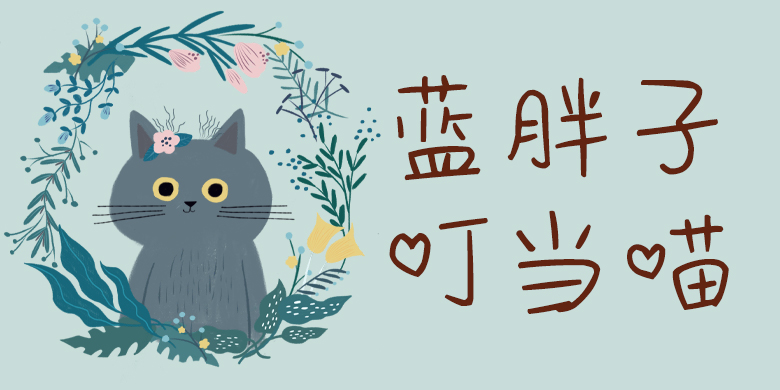
方正手迹-蓝胖子叮当喵
方正手迹-蓝胖子叮当喵,这款字体结构工整、笔画清晰,兼顾美观与易读性,适用于标题、正文、海报、包装、LOGO 等多种场景。字形优雅稳定,风格百搭耐看,适配日常排版与创意设计,让文字呈现更舒适、更具质感。方正手迹-蓝胖子叮当喵一笔一画,皆是细节,以均衡的比例、流畅的线条打造舒适视觉体验,字形端正大气,风格简约现代。无论是商业设计、品牌宣传还是日常排版,都能轻松驾驭,让文字更有格调与力量。方正手迹-蓝胖子叮当喵字体下载。
化点为心,笔画简洁流畅,单纯可爱,字里行间藏不住的爱心,满满的少女气质。